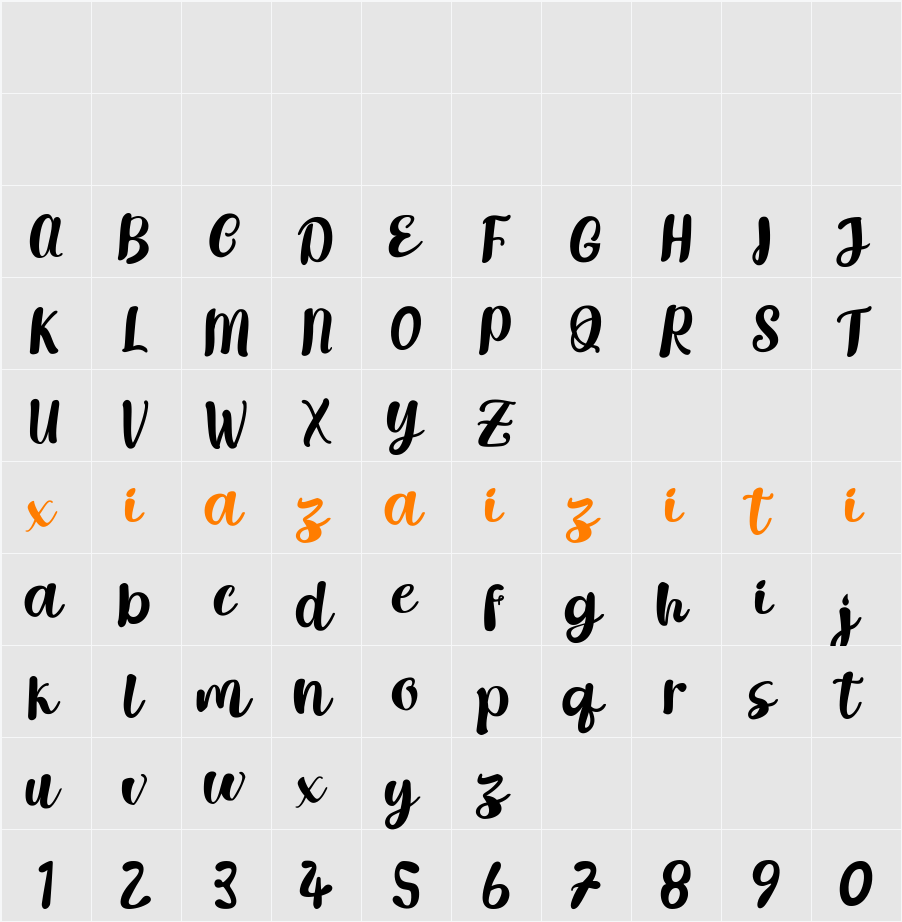
Zigasto
Zigasto,这款字体结构工整、笔画清晰,兼顾美观与易读性,适用于标题、正文、海报、包装、LOGO 等多种场景。字形优雅稳定,风格百搭耐看,适配日常排版与创意设计,让文字呈现更舒适、更具质感。Zigasto一笔一画,皆是细节,以均衡的比例、流畅的线条打造舒适视觉体验,字形端正大气,风格简约现代。无论是商业设计、品牌宣传还是日常排版,都能轻松驾驭,让文字更有格调与力量。Zigasto字体下载。